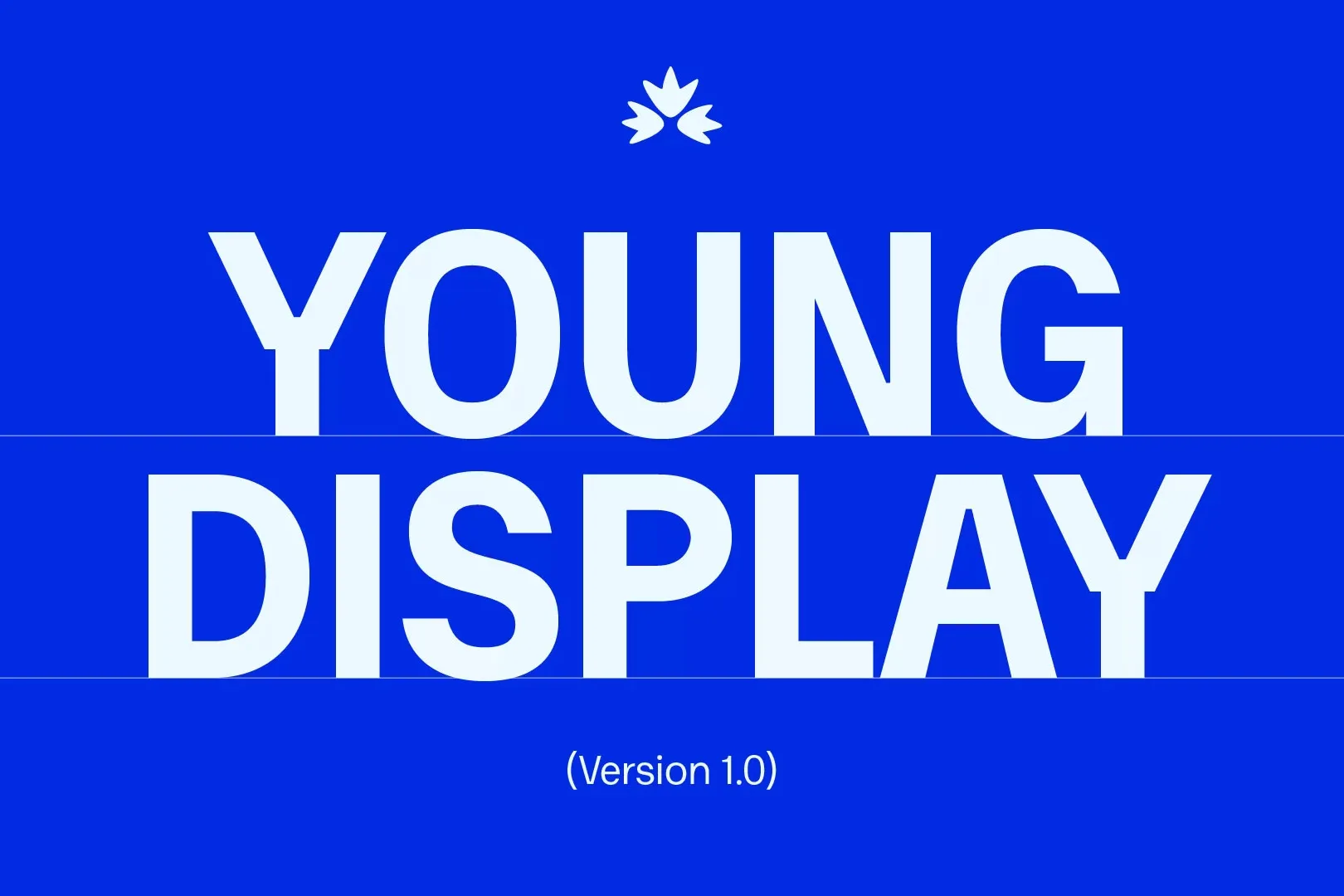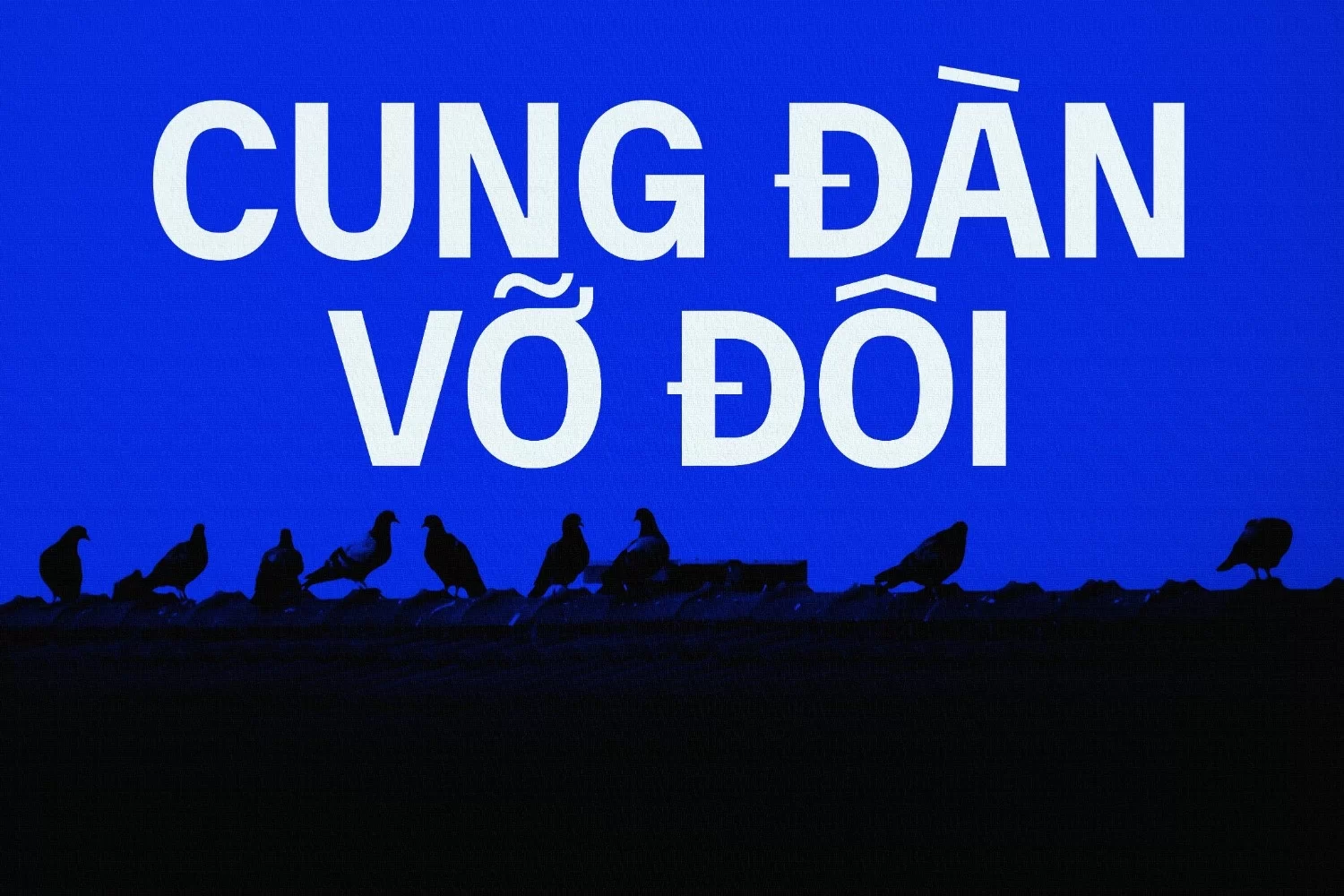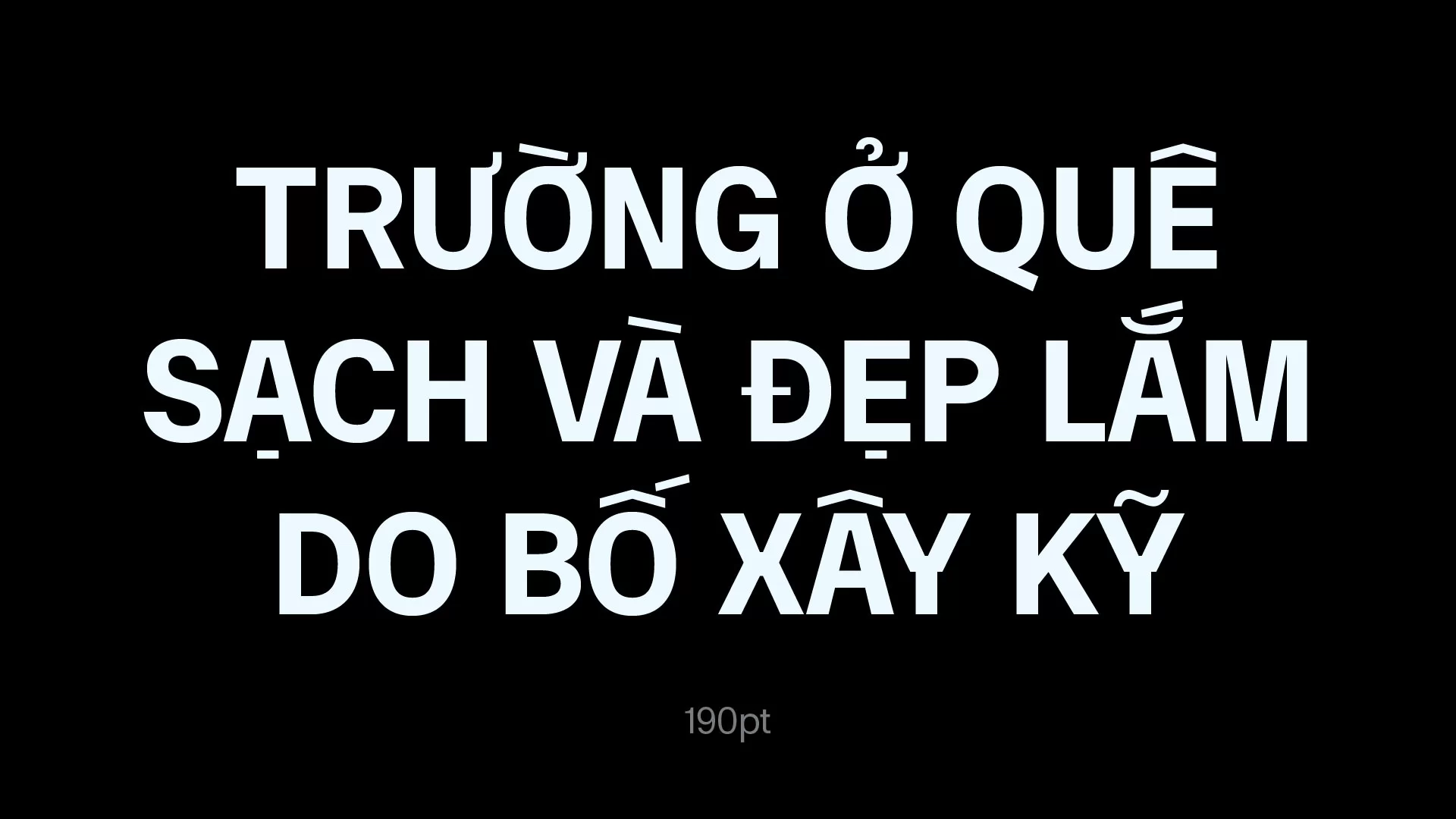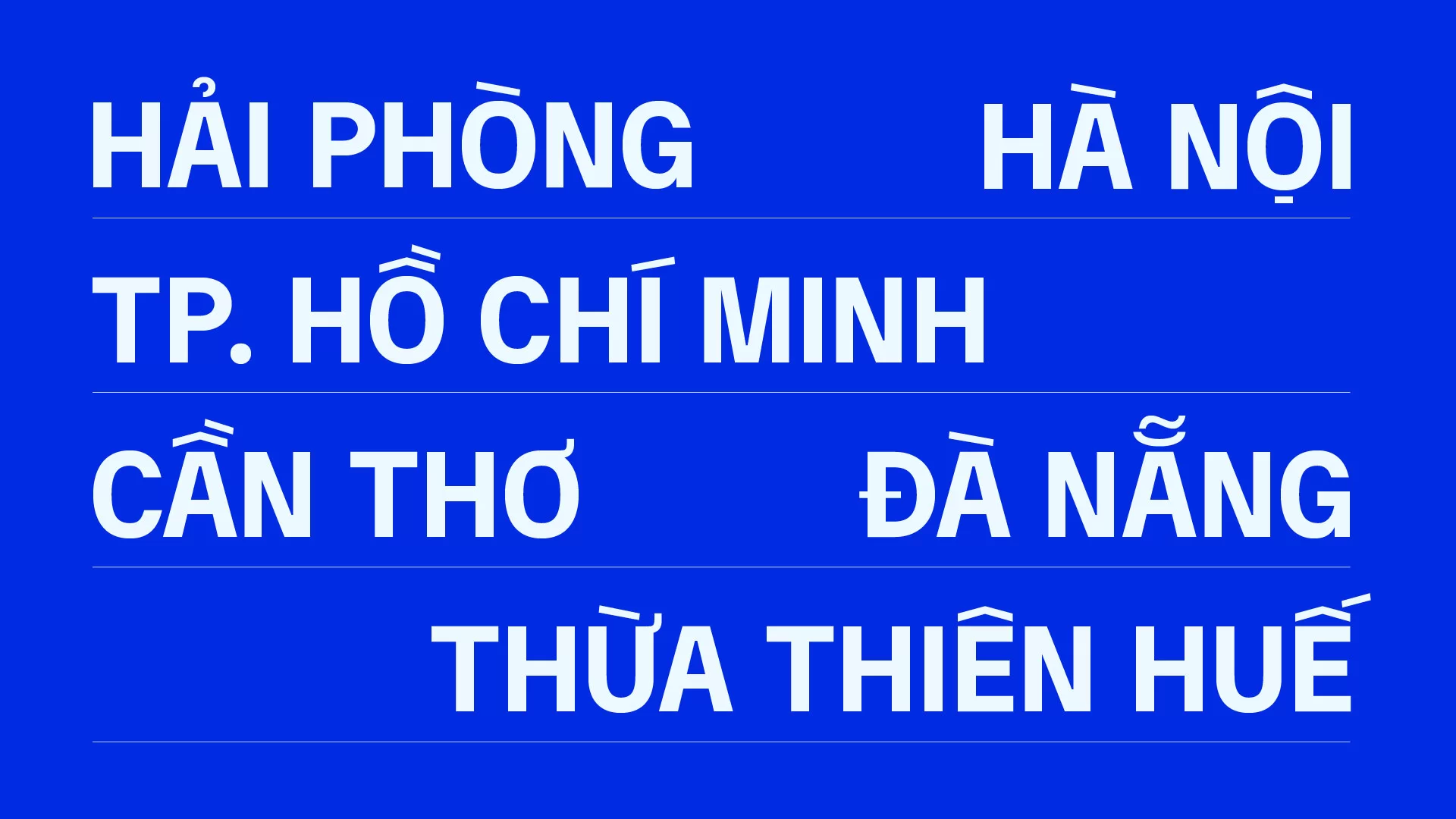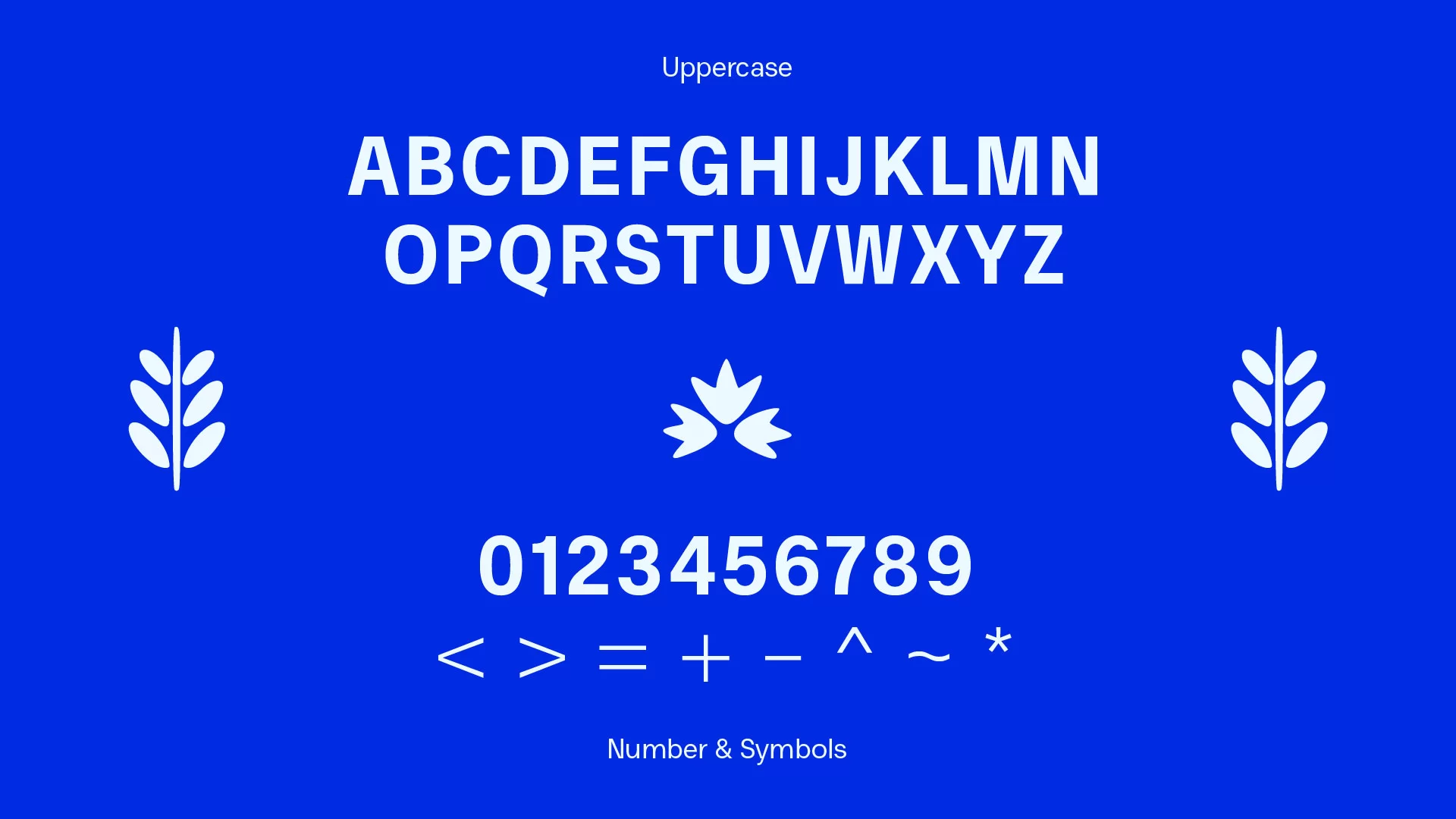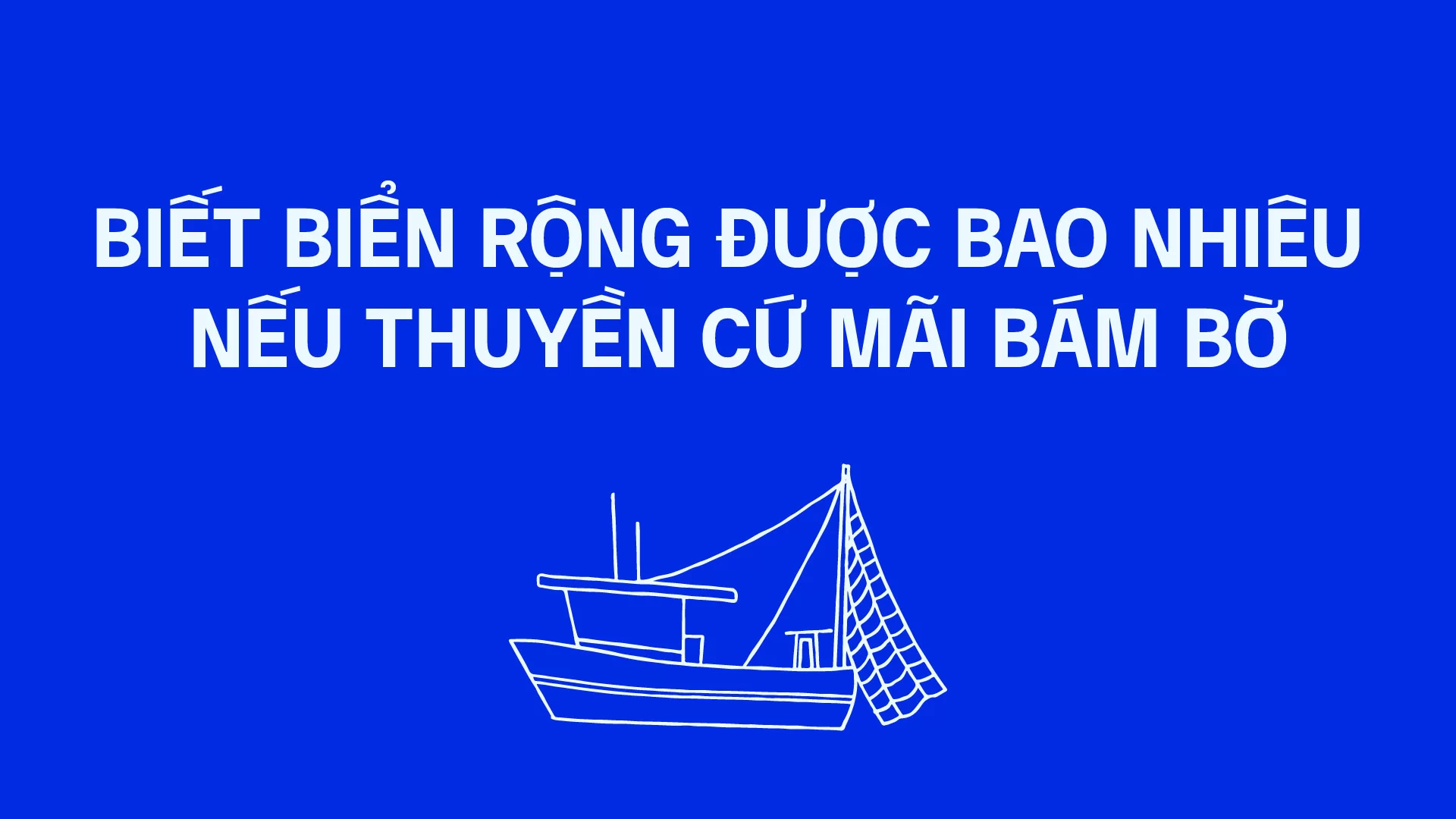
Young Typeface – Font Display tiếng Việt miễn phí
Young Display là phiên bản đậm và cá tính hơn từ bản gốc — mạnh mẽ, rõ nét và giàu biểu cảm. Trọng lượng lớn, dấu được tinh chỉnh cho tiếng Việt, hình dáng dứt khoát giúp font nổi bật trong tiêu đề và nhận diện. Mang tinh thần rõ ràng, cá tính và hiện đại.